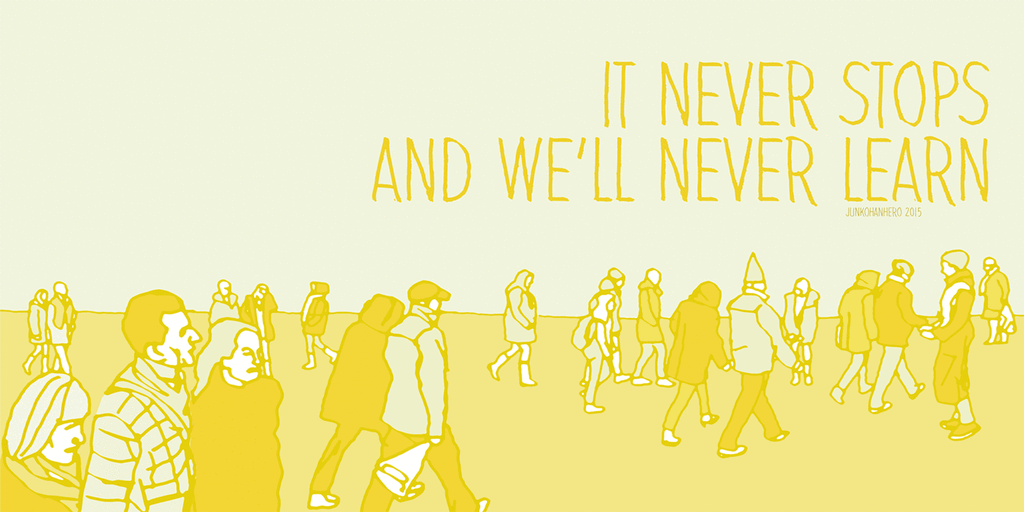
A It never stops and we’ll never learn Font é uma elegante fonte escrita à mão criada pelo designer Hamilton. Esta tipografia abrange várias cores e traços fluidos, oferecendo um toque de originalidade e personalização para projetos digitais. Inspirada em textos escritos a garrafone, esta fonte se destaca por sua versatilidade, adequando-se perfeitamente tanto a design gráfico como à criação de mensagens criativas nas redes sociais. A It never stops and we’ll never learn é perfeita para quem busca uma fonte diferente que traga um toque único aos seus designs e publicações online.